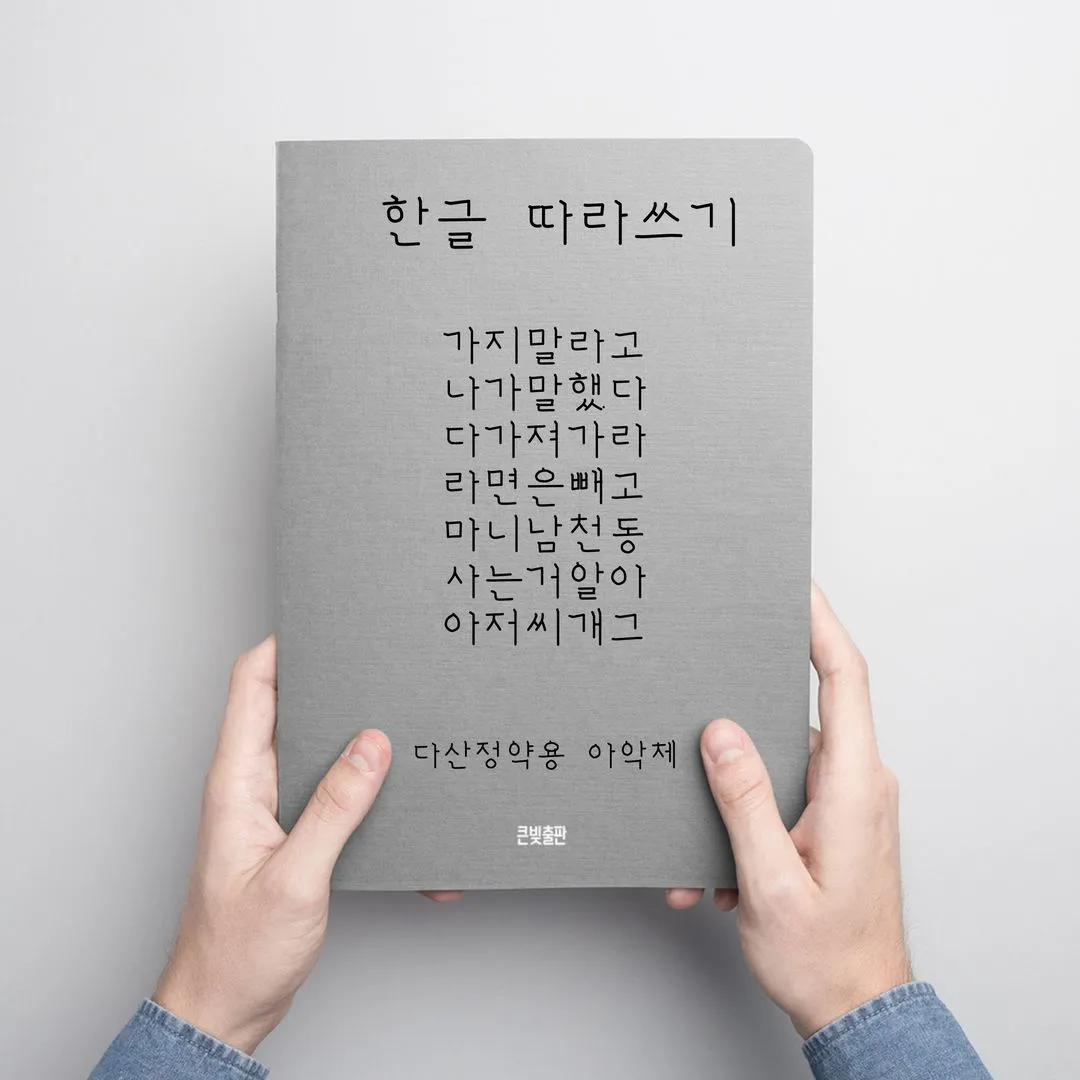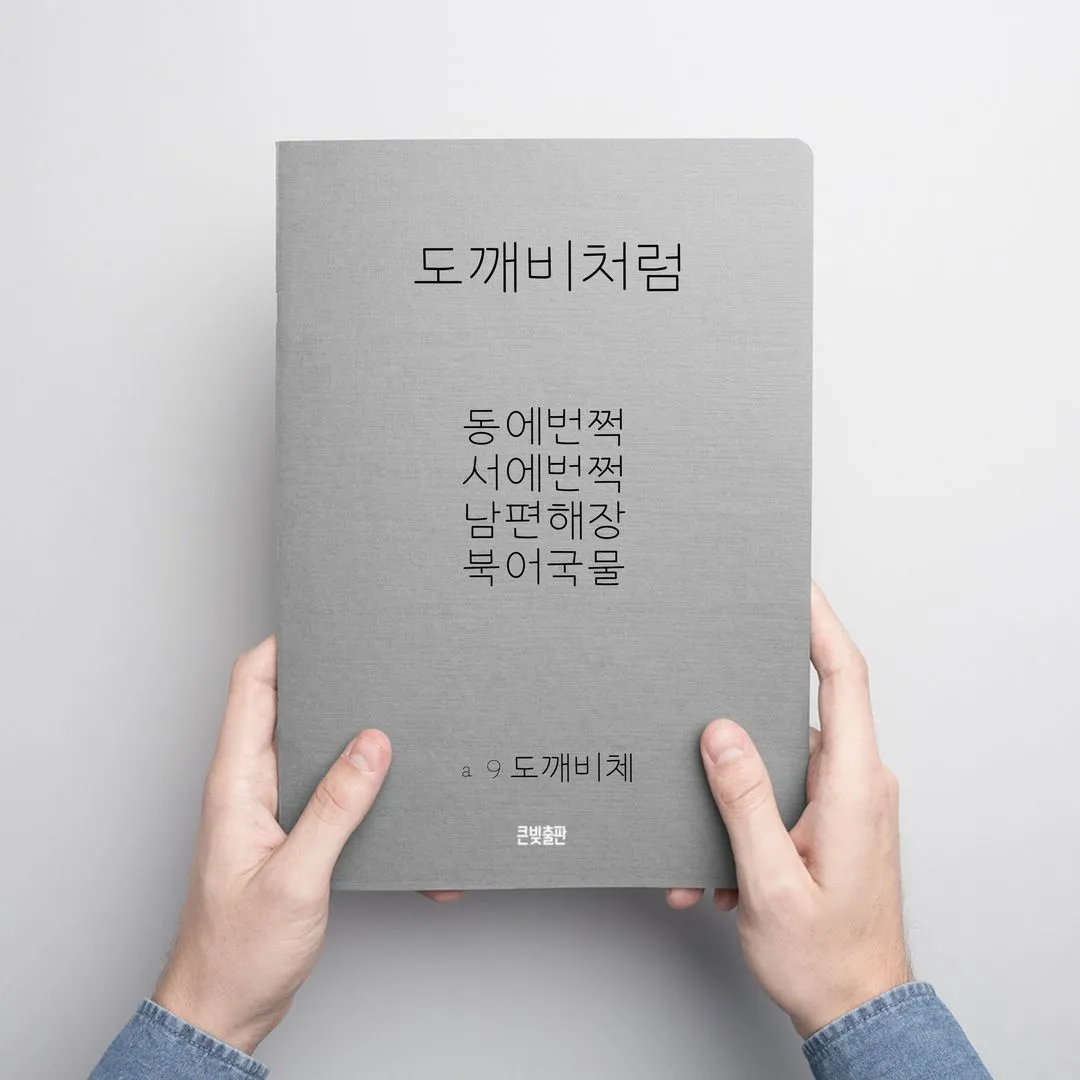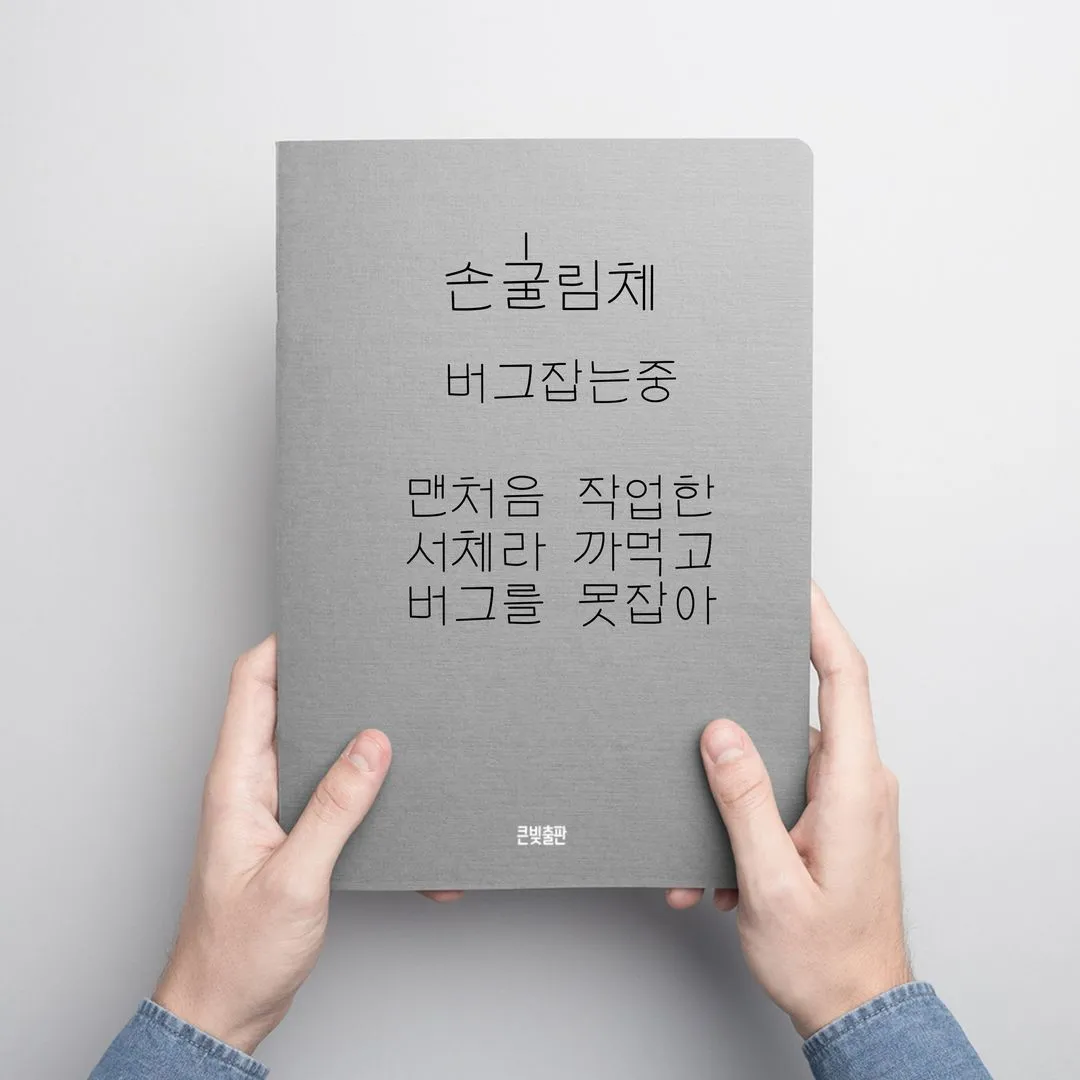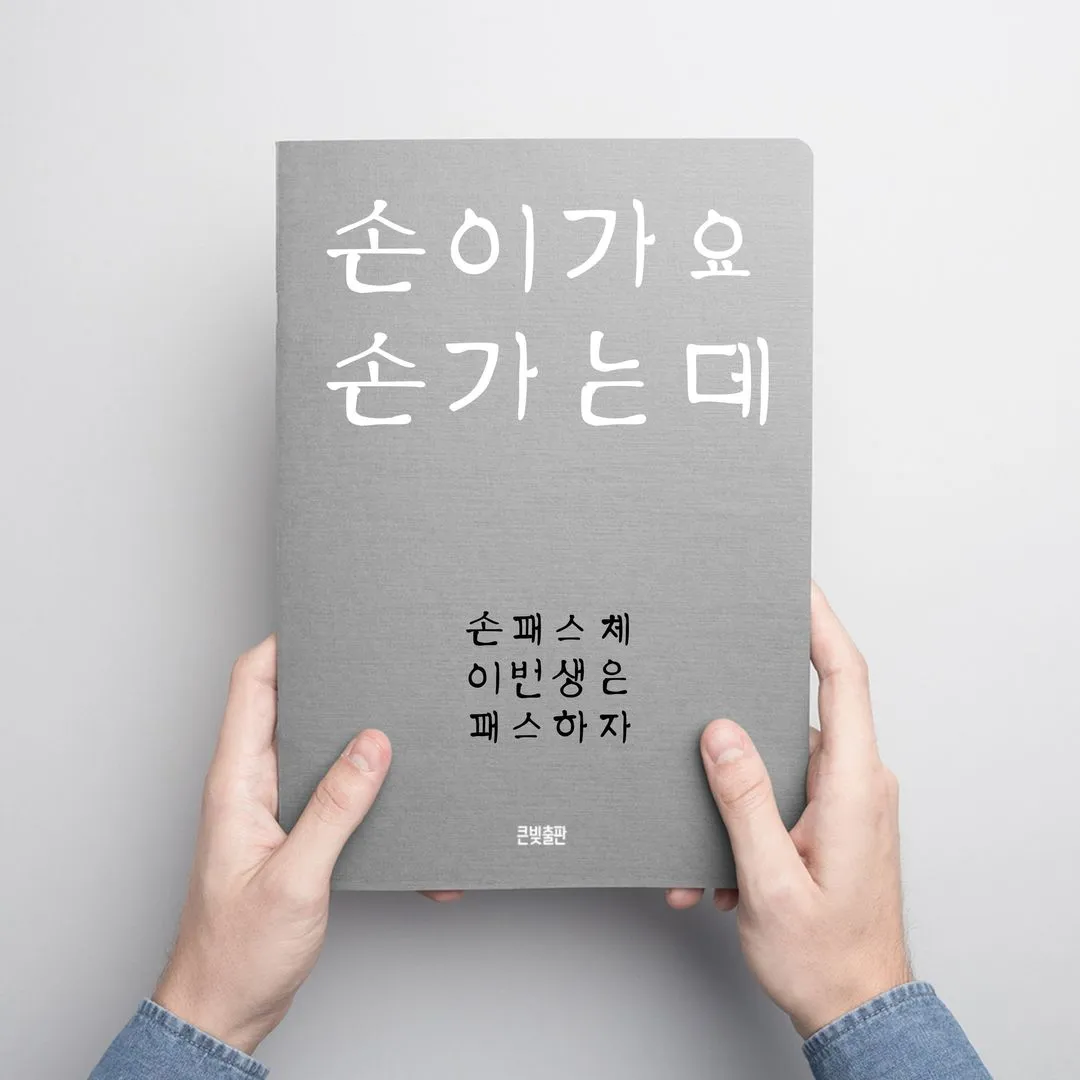
a9폰트 – 그동안 만들었던 폰트 샘플
AI가 한거 아님 그냥 사람이 잠깐 한 것입니다. 111,172+영문+숫자+약물은 기본 한글날까지 완성은 아직 모르겠지만 일단 하나에 집중해서 마무리 예정입니다. 그동안 만든 서체는 5개로 손굴림체, 손패스체, 도깨비체, 손맘서체, 다산정약용 아악체
익숙한 독자의 글씨로 전자책이나 굿노트 필기를 하거나 인터넷에 쓰거나 댓글 달았던거 다 수집해서 본인의 책을 만들어주는 서비스를 제공하려고 합니다. 출판사 굿즈는 출판사가 만들어야!
한글날 공개가 가능할지… 많이도 만들어봤습니다.
가나다라마바사아 차라마폰트
다산정약용 아악체
도깨비체 동서남북 동서남북 응?!?
손이 가는데가 손패스체
손맘서체… 내맘이야 니맘을 내가 알게 뭐야…
손굴림체… 안굴러… 버그잡는중…